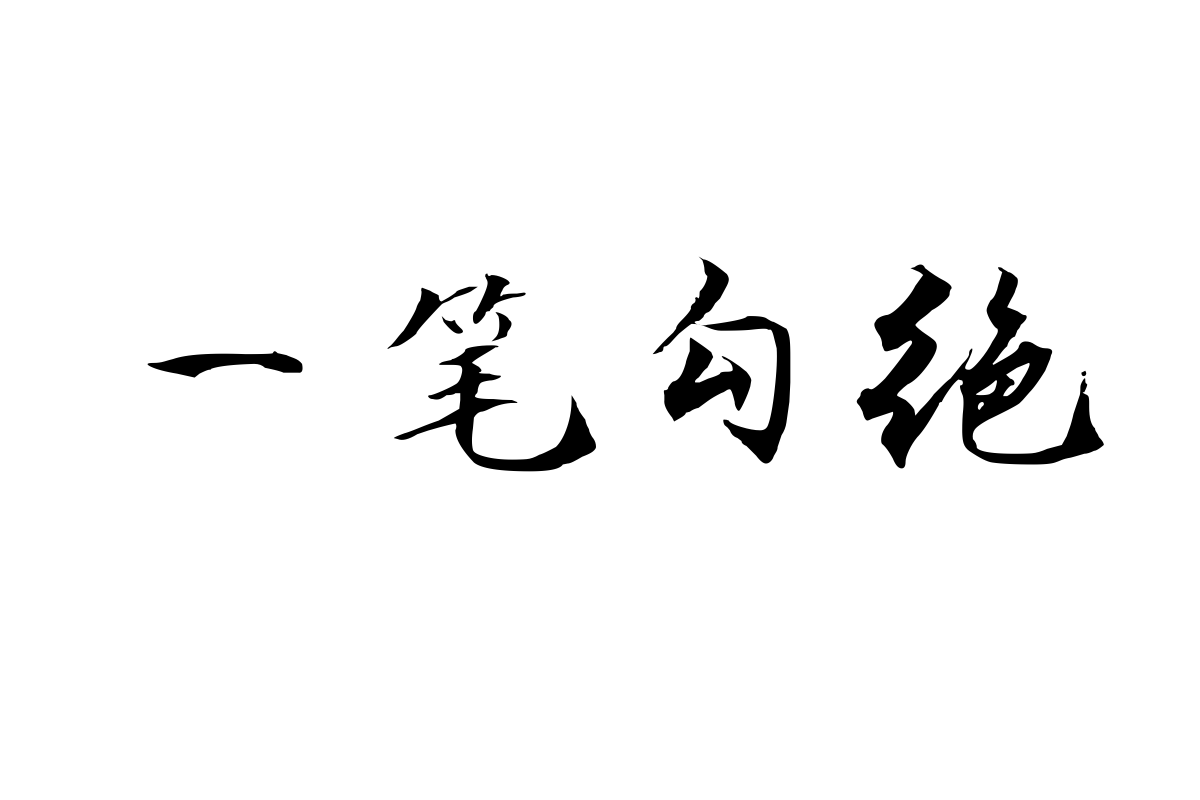
三极灵飞体是一款具有独特风格的中文字体,由设计师精心打造而成。这款字体以其独特的笔画结构和流畅的线条而闻名,给人一种优雅、灵动的感觉。
三极灵飞体的笔画粗细适中,既不会过于粗犷也不会过于细弱,使得整体看起来既富有力度又不失柔美。同时,该字体的字形结构紧凑,线条连贯,使得整个字体看起来更加协调统一。
在设计上,三极灵飞体采用了简洁明了的设计风格,没有过多的装饰元素,但每一个细节都经过精心设计,展现出一种简约而不简单的美感。这使得它在视觉上给人一种清新、自然的感觉,让人一眼就能感受到其独特的魅力。
总的来说,三极灵飞体是一款非常优秀的中文字体,无论是用于书籍、杂志还是网页设计,都能展现出其独特的风格和韵味。